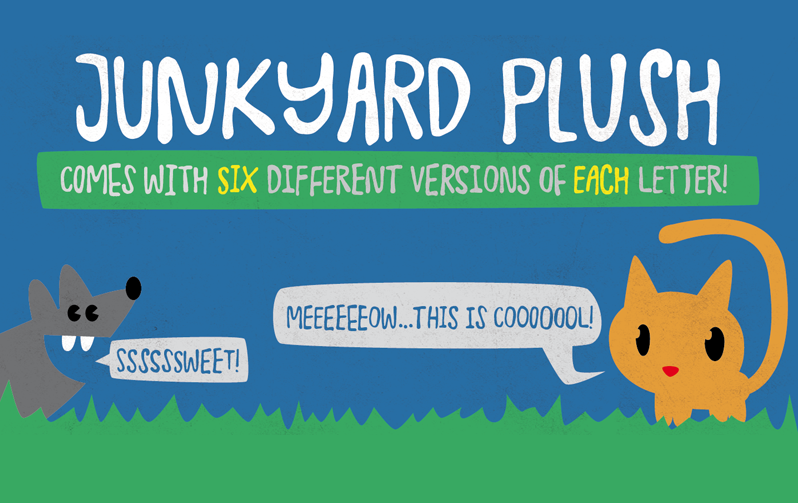
Junkyard Plush Font – Fonte Grátis
Junkyard Plush Font
A fonte Junkyard Plush é uma excelente escolha para designers que procuram texturas únicas e autênticas para seus trabalhos. Com seis versões diferentes por letra, ela oferece muitas possibilidades criativas, especialmente quando se trata de alternâncias contextualizadas. Essa característica permite que seu texto pareça aleatório e verdadeiramente feito à mão, um aspecto muito valorizado nas obras digitais. Além disso, a font inclui ligaturas para letras duplas, garantindo uma aparência ainda mais natural e realista. A designer Pizzadude.dk nos apresenta esta fonte de forma cuidadosa e detalhada, permitindo que o criativo aproveite as nuances desta fonte enquanto mantém uma aparência verdadeiramente autêntica. A Junkyard Plush é perfeita para designers digitais em busca de dar um toque único aos seus projetos visuais, seja para textos legíveis ou gráficos 3D que buscam uma sensação única e autoral.